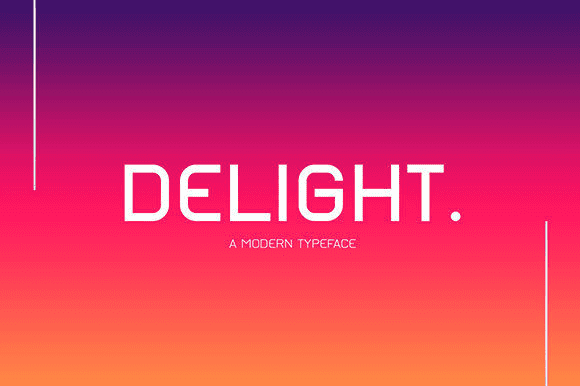
Шрифт Delight - это современный шрифт без засечек.
Подходящий для широкого спектра дизайнов благодаря своему аккуратному и простому стилю, этот шрифт имеет потенциал стать Вашим любимым шрифтом, неважно по какому поводу!